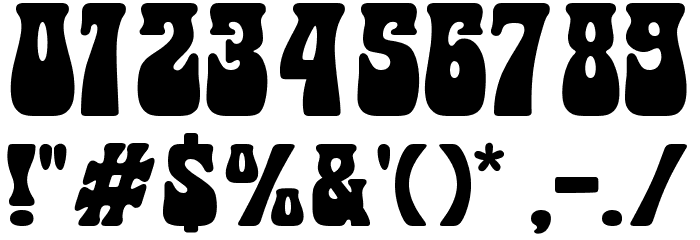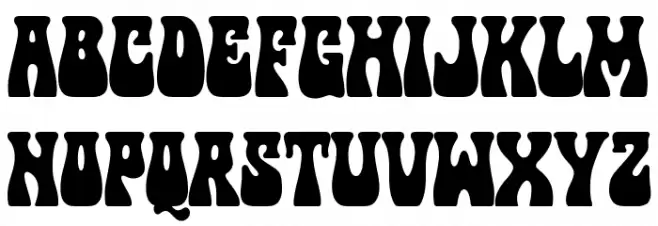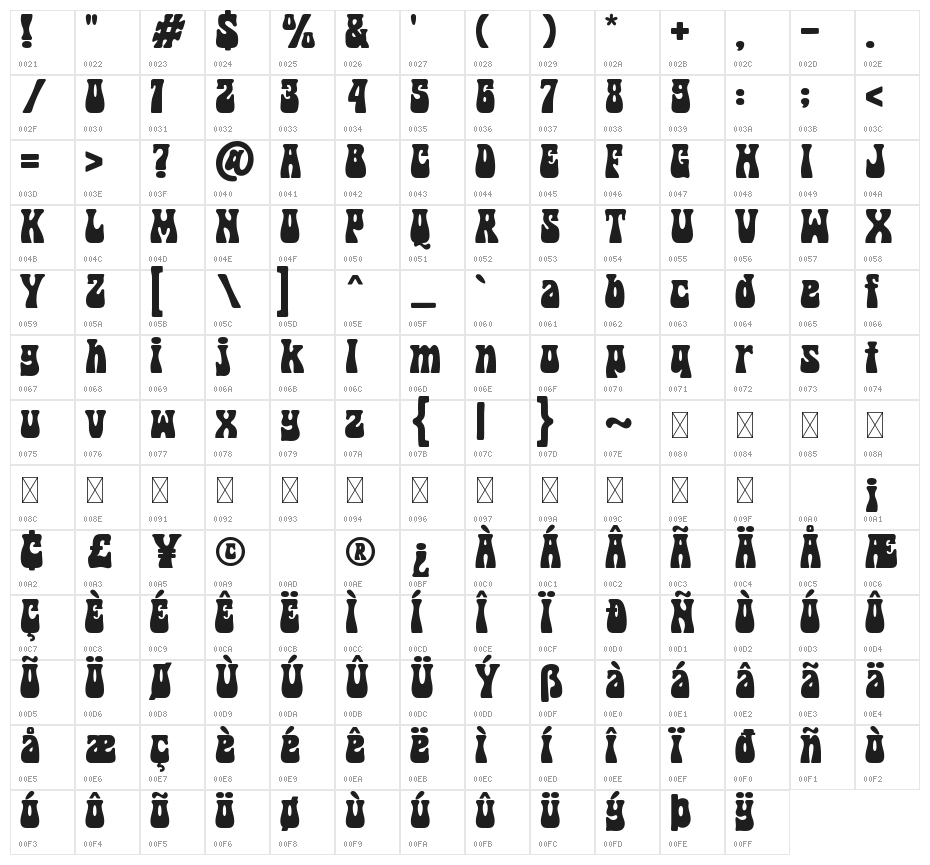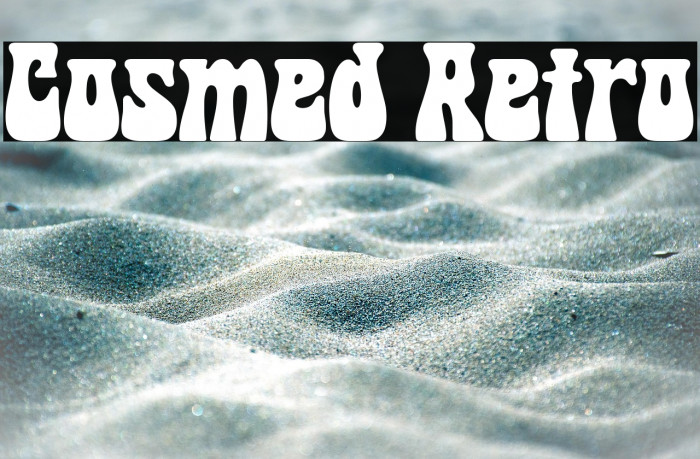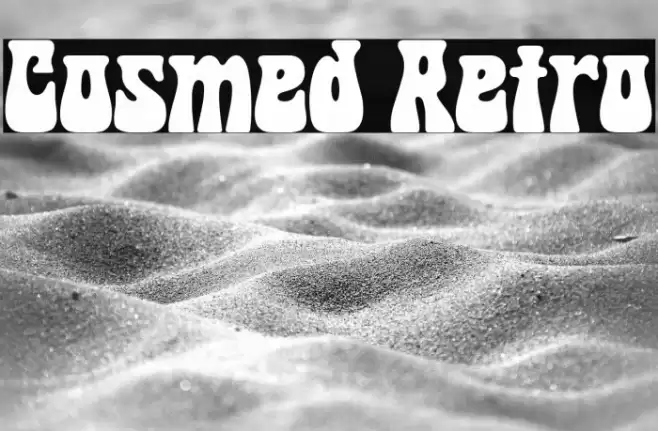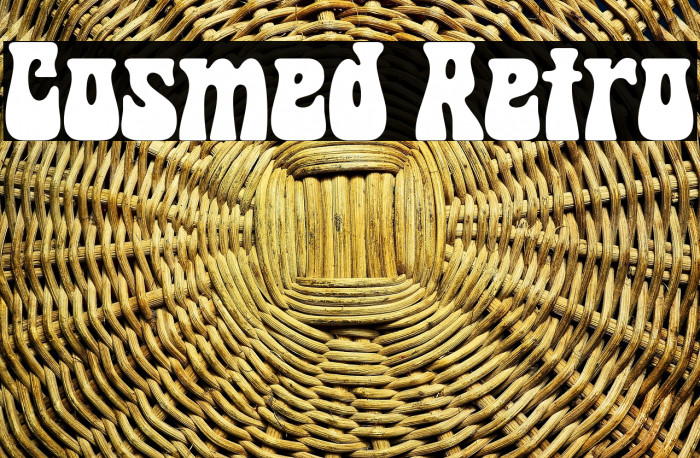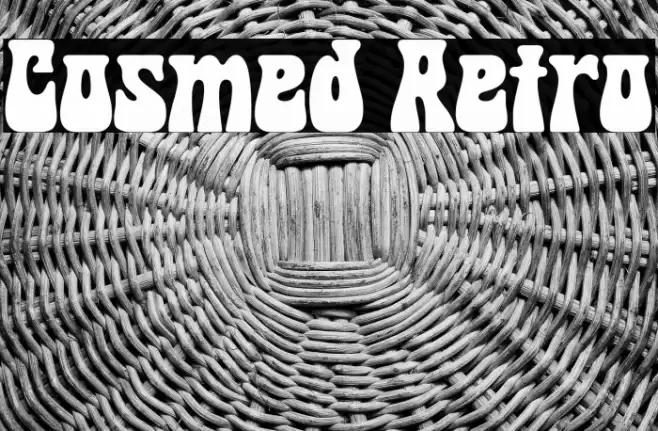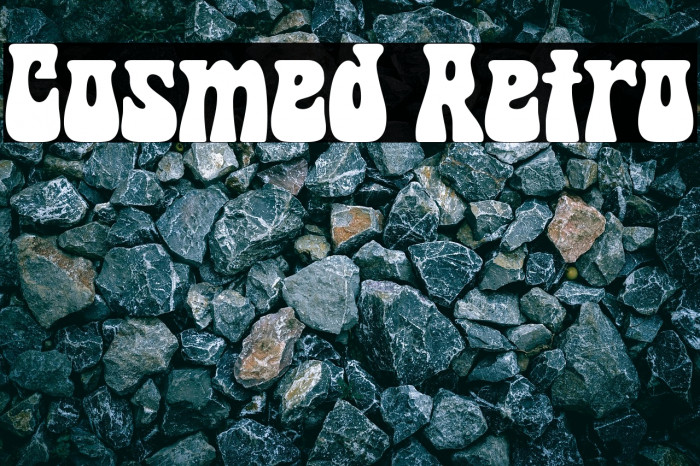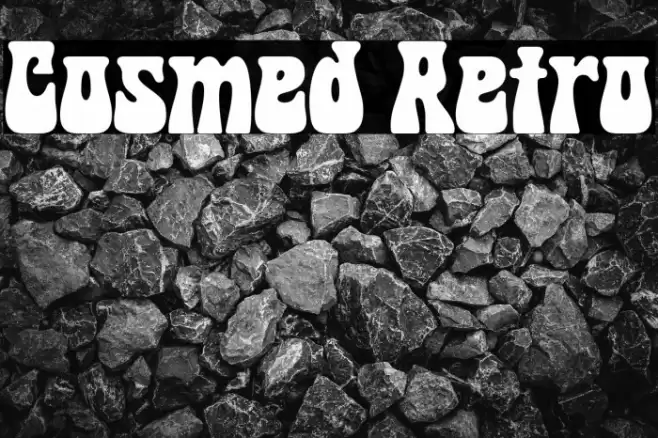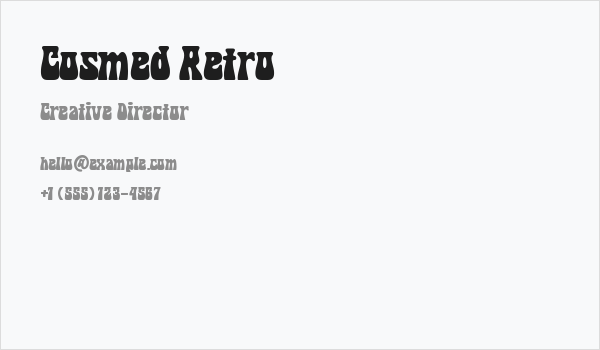
Cosmed Retro Font
| Estilo general | Retro, Playful |
| Proyectos propuestos | Ideal for vintage-themed posters, playful branding, children's book covers, and retro-style advertisements. |